今回は、水曜日クラスの硬筆展練習作品をご紹介します。練習を重ねる中で、一人ひとりの文字が少しずつ整い、それぞれの頑張りが感じられる作品がそろいました。どうぞごゆっくりご覧ください。
水曜日 2年生
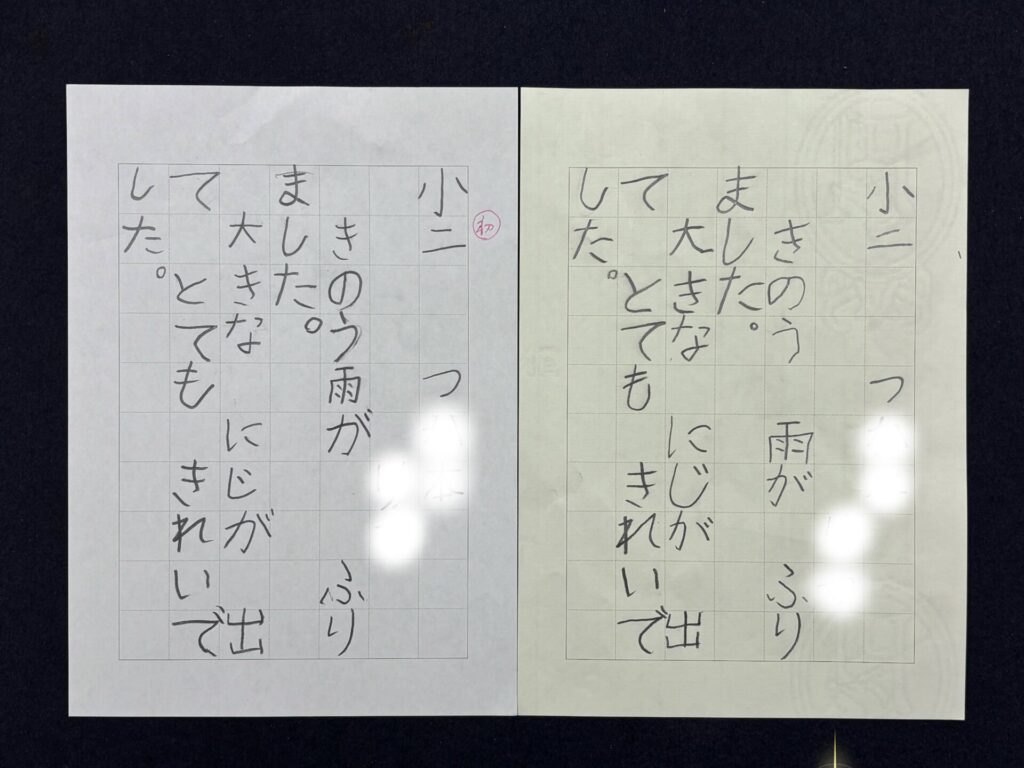
字をしっかり観察し、形を捉えて書けるようになりました。一本一本の線がしっかりしてきて、文字全体がぐんと安定してきました。濃く大きく、マスの中でバランスよく書けるようになった、まとまりのある作品です。
水曜日 3年生
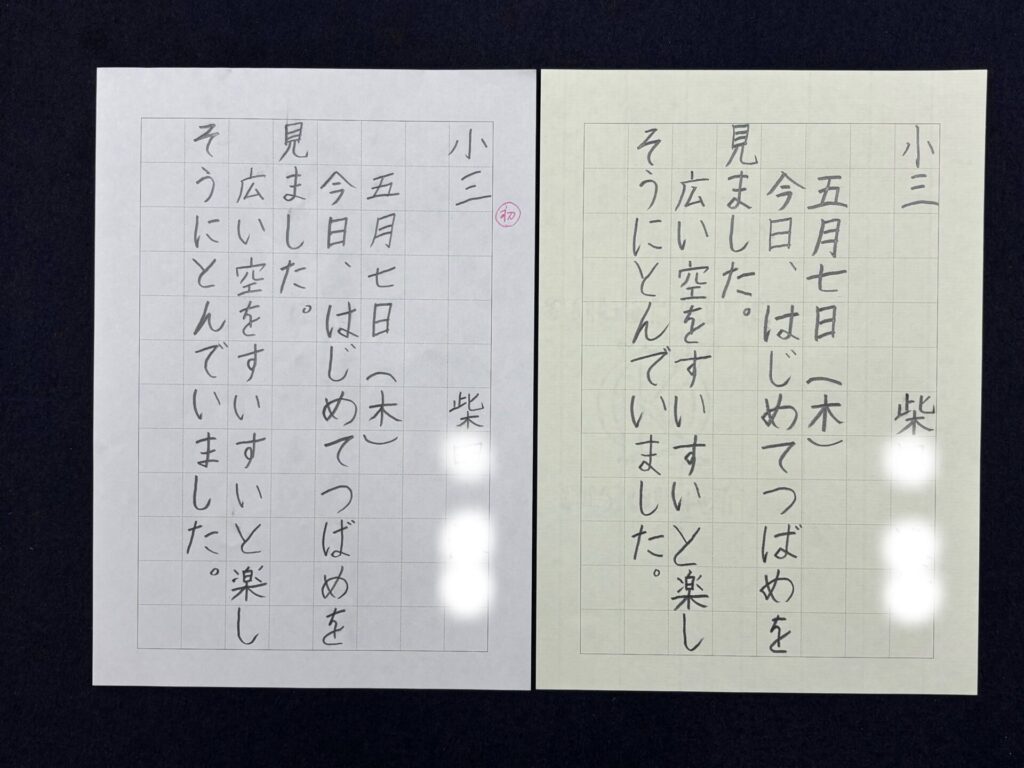
一筆一筆がなめらかでのびのびとした字に変わり、文字全体が落ち着いて見えるようになりました。ひらがなのやわらかな表情もきれいに出ていて、行の流れがすっきり整った作品です。名前も上手に書けるようになりました。
水曜日 6年生
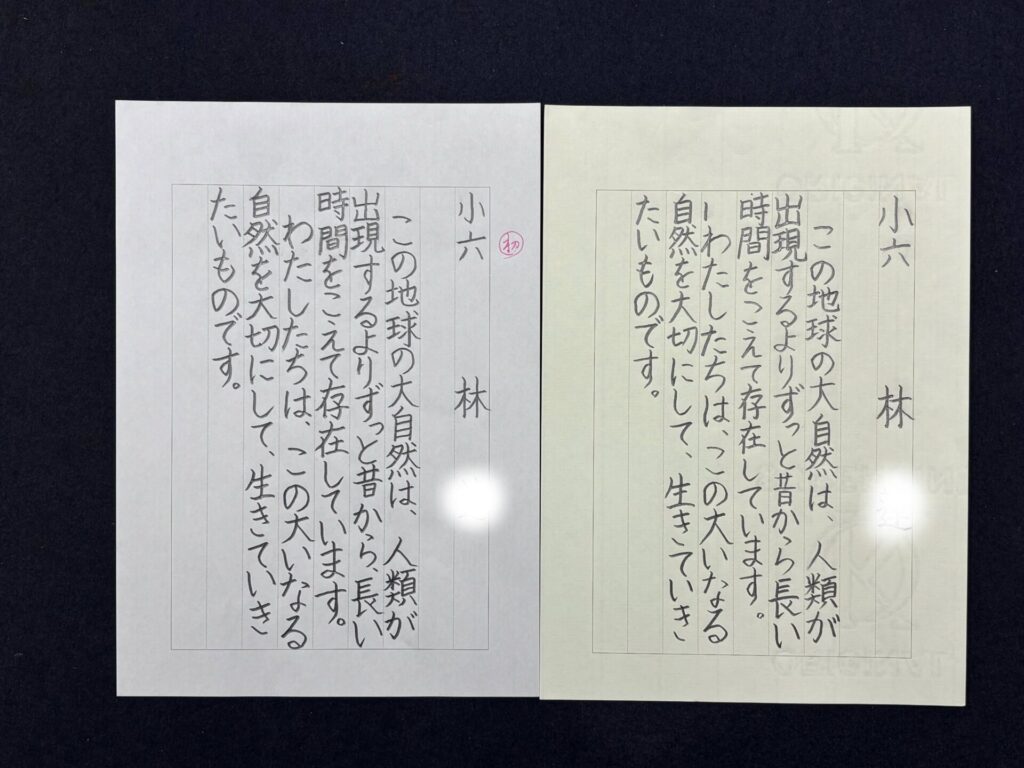
一文字ずつの形が美しく、作品全体として力強い、とても目をひく作品です。字間や行の流れがすっきりまとまり、漢字とひらがなの大きさも考えられた読みやすい作品に仕上がりました。
水曜日 4年生
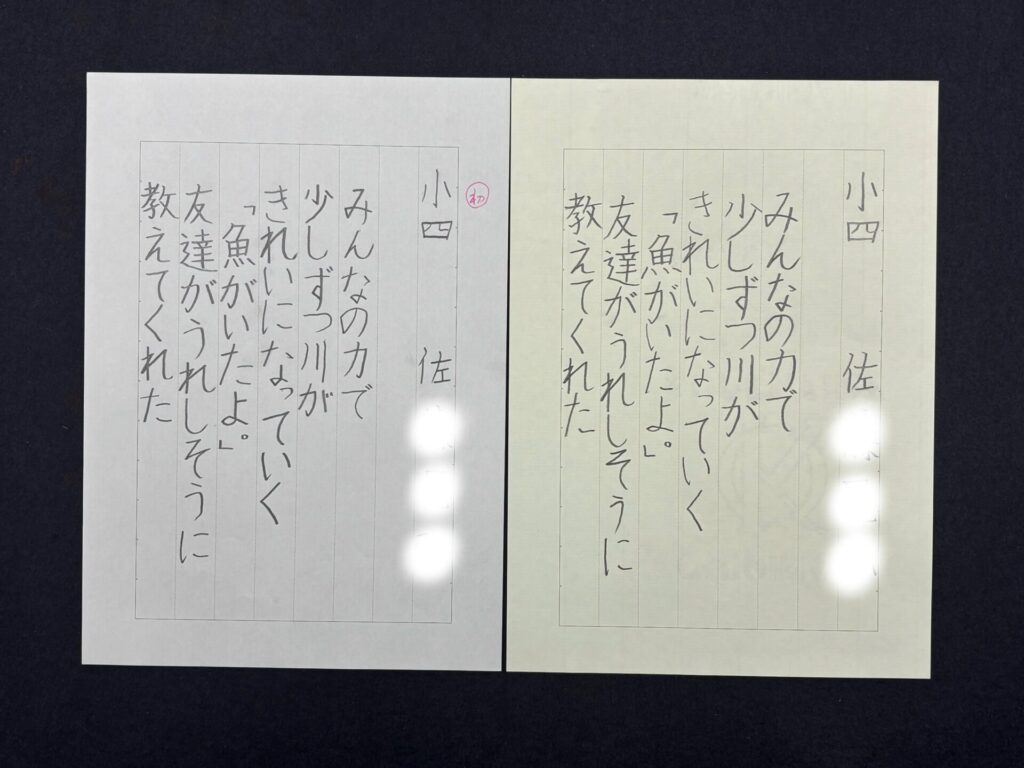
作品全体が大きく、とてものびやかに書けています。最初の作品と比べると、清書は一画一画に落ち着きが出て、文字の形や字間のバランスもよくなりました。名前もたくさん練習して、美しく整えて書けるようになりました。
水曜日 4年生
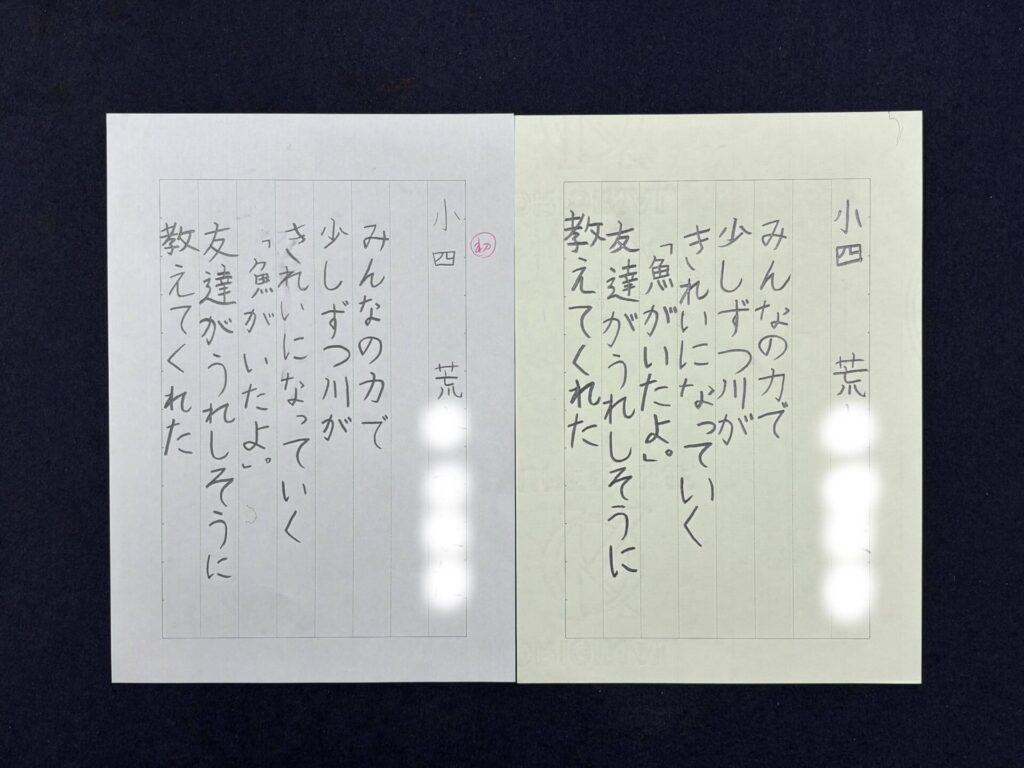
一文字ずつの形と大きさが整い、線にも力強さと安定感が出てきました。文字の中心がそろって行の流れがなめらかになり、全体がぐっと締まった作品になりました。名前も頑張って練習していたのが印象的でした。
水曜日 4年生
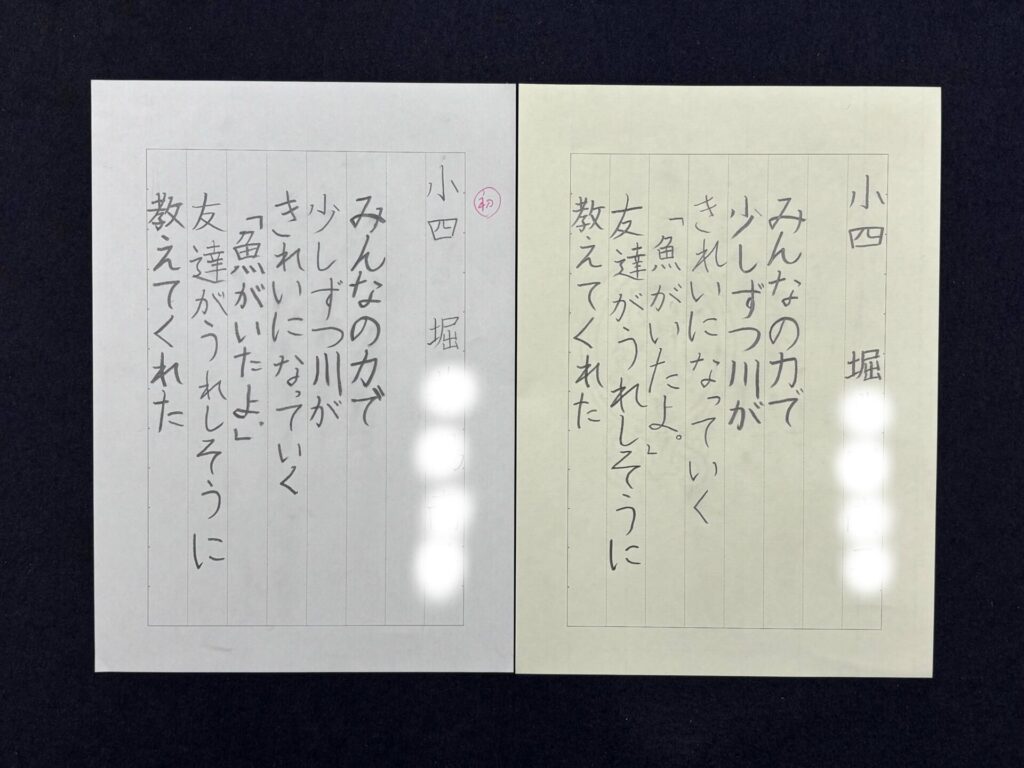
一画一画を確認しながら書き、最初と比べると文字の形がぐっと整いました。中心がまっすぐそろい、字の間隔や大きさも安定して、行の流れが美しい作品に仕上がっています。
水曜日 6年生
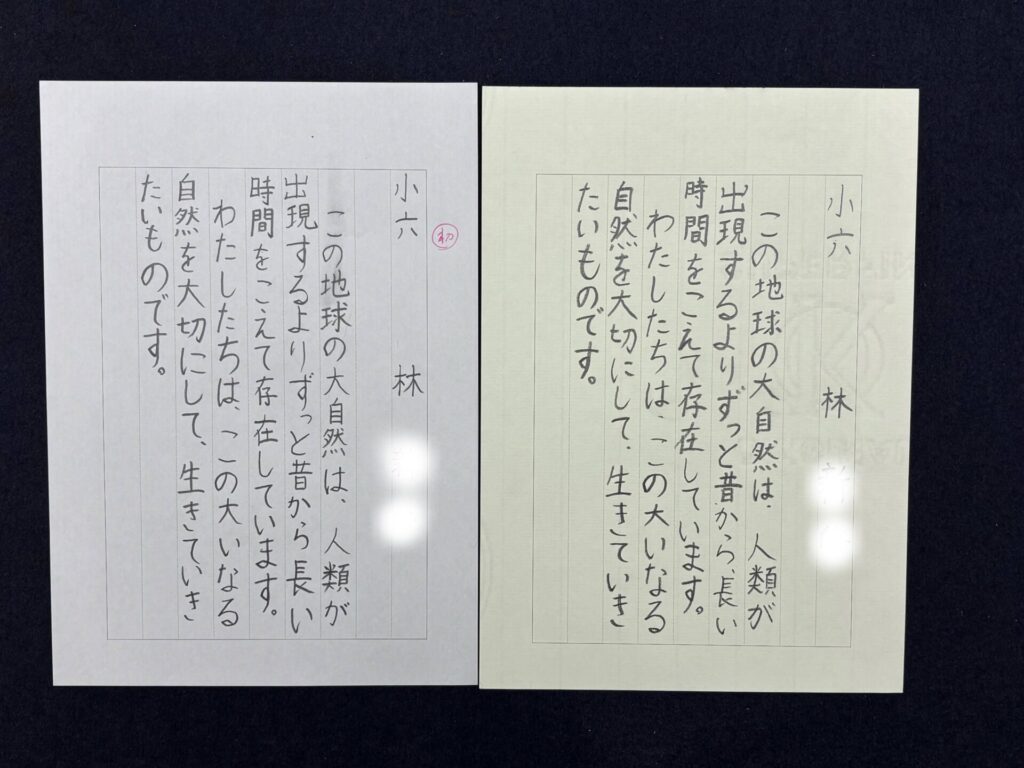
最後の一枚は、漢字とひらがなの大きさ、形が整いました。線にも力強さが加わって、全体がきりっと引き締まった目に飛び込んでくるような作品に仕上がっています。
水曜日 5年生
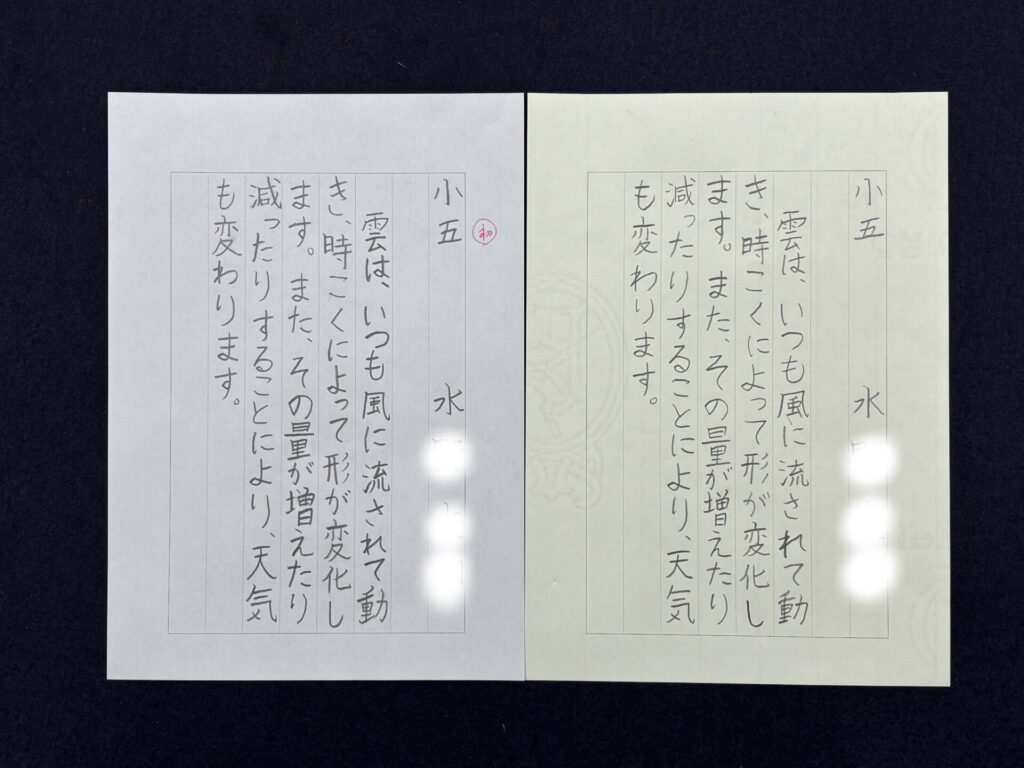
線がしっかりとして、文字全体に安定感が出てきました。漢字とひらがなのバランスも整い、中心を意識して書けています。行の流れがまっすぐ美しく見える作品になりました。
どの作品も、それぞれの頑張りと成長が感じられる作品に仕上がりました。くり返し練習する中で、少しずつ文字が整っていく様子はとても頼もしく、最後までていねいに書こうとする気持ちがしっかり伝わってきます。水曜日クラスのみなさん、よく頑張りました。